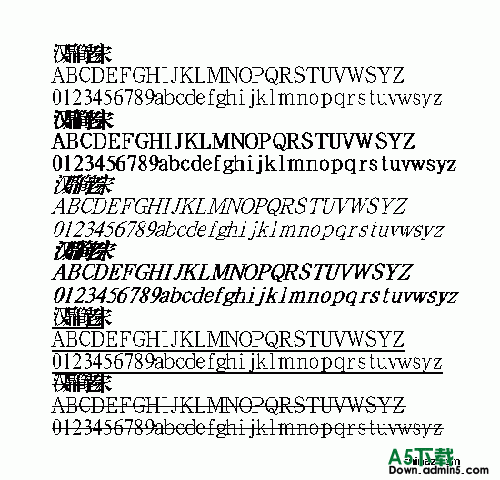
漢鼎簡(jiǎn)老宋字體是一款用于美工設(shè)計(jì)方面的字體,適合學(xué)習(xí)美工作業(yè)的朋友們使用,它雖然表現(xiàn)的形式比較特殊,但是在有些環(huán)境下還是能夠展現(xiàn)出完美的特色的,有需要的朋友可別錯(cuò)過(guò)了,綠色資源網(wǎng)提供最新中文字體和英文字體免費(fèi)下載。